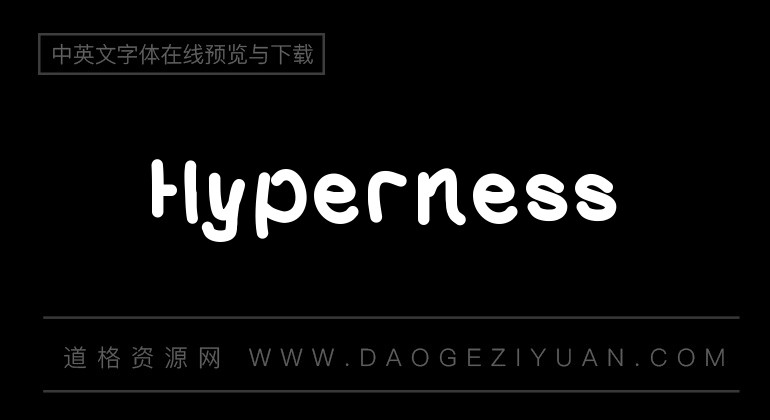
Hyperness 字体是一款由著名设计师 Alex Griendling 创作的复古风格字体。它具有超高的弹性,细节丰富,拥有强烈的表现力。Hyperness 字体的字符设计完美融合了经典的复古风格与现代设计,让字体拥有灵动的外观,可以让您的设计更加吸引人。Hyperness 字体可以用于各种设计,从海报、标志到书籍封面等,都可以添加一些复古的色彩,让您的设计更加有趣。内容介绍
Hyperness是一款非常不错的手写艺术字体,具有很好的视觉感,适合于文化类的宣传设计、商业类品牌的广告和产品包装设计以及个性化文字排版等较多场景。